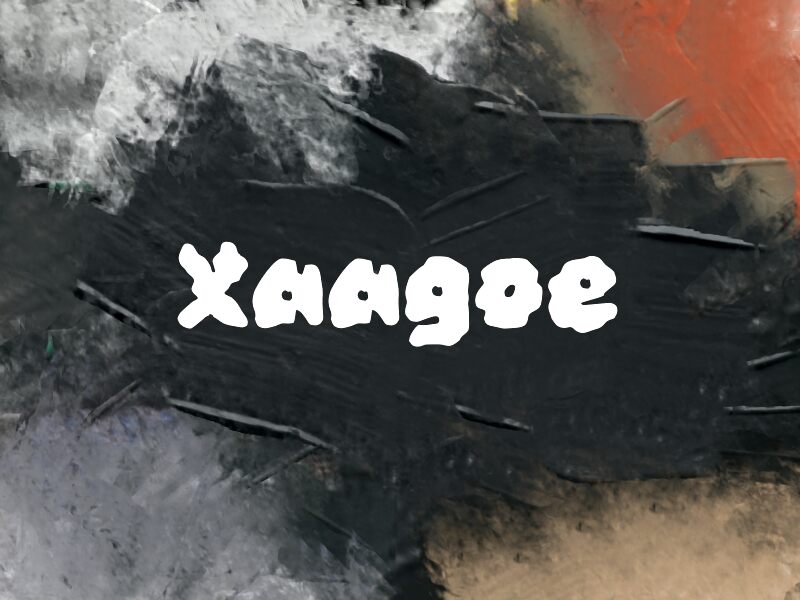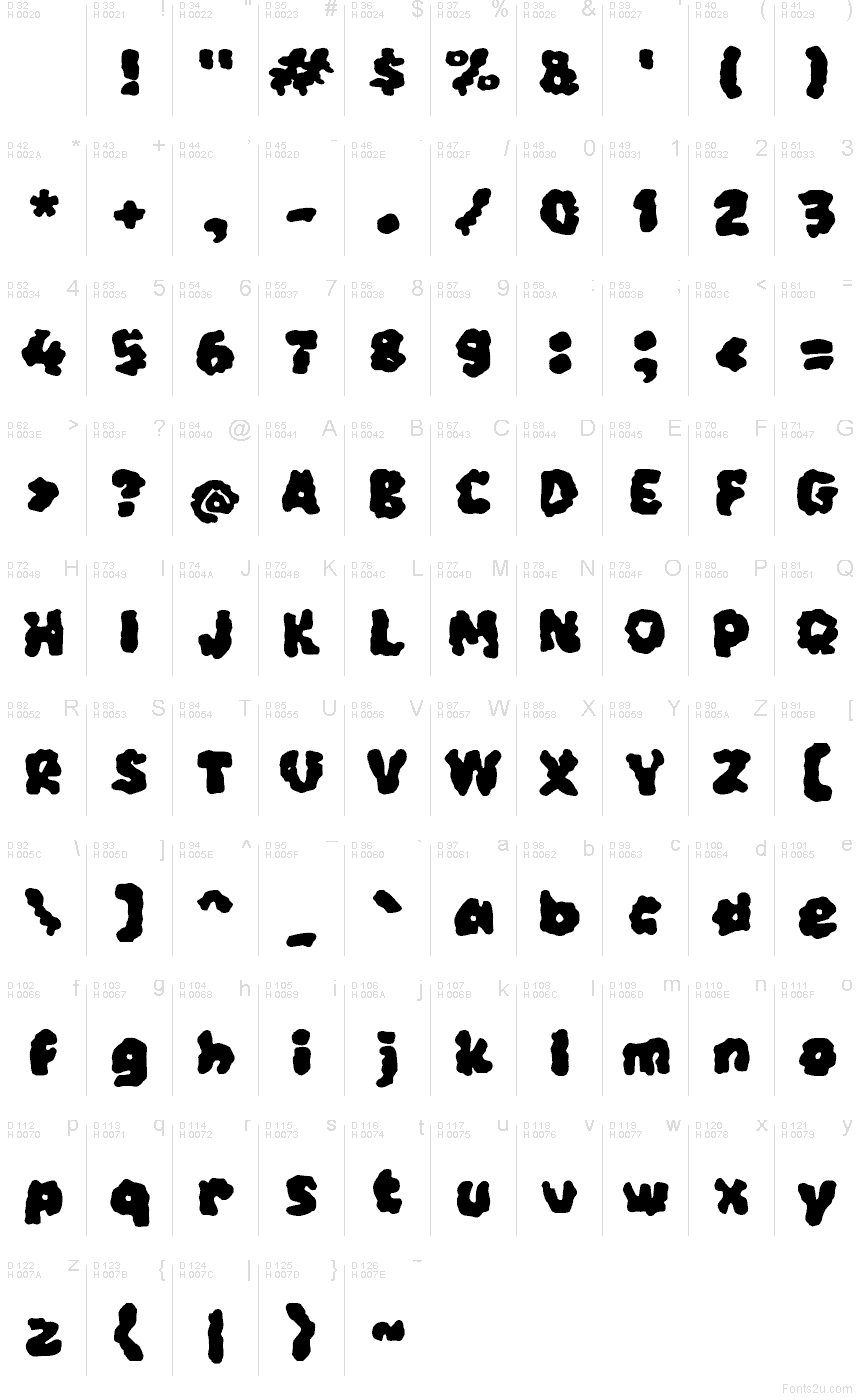
Xaagoe
Xaagoe de Wep es una tipografía display de estilo cartoon gratuita, con una silueta hinchada y asimétrica que parece más moldeada que dibujada. Su masa negra redondeada, los pequeños huecos y un ritmo ligeramente irregular le dan a las letras una presencia suave y orgánica, alejándose del estándar de las fuentes tipo burbuja.
Esta suavidad visual encaja a la perfección en pósteres infantiles, empaques de juguetes, invitaciones de cumpleaños, diseños de pegatinas y títulos de juegos, donde el texto debe sentirse como parte de la ilustración. Es ideal para titulares cortos y logotipos, ya que sus contornos irregulares mantienen la tipografía llena de vida incluso con pocas palabras.